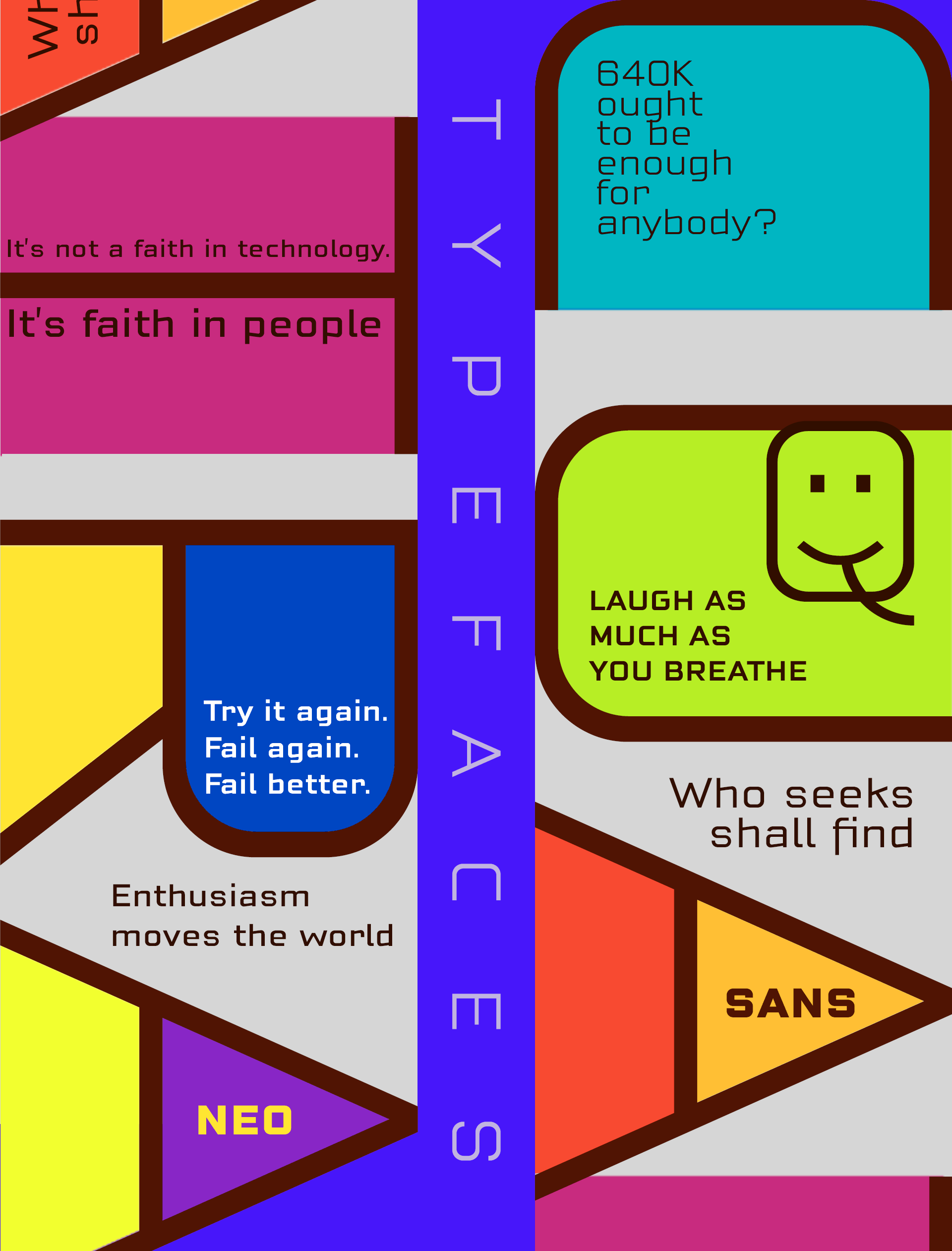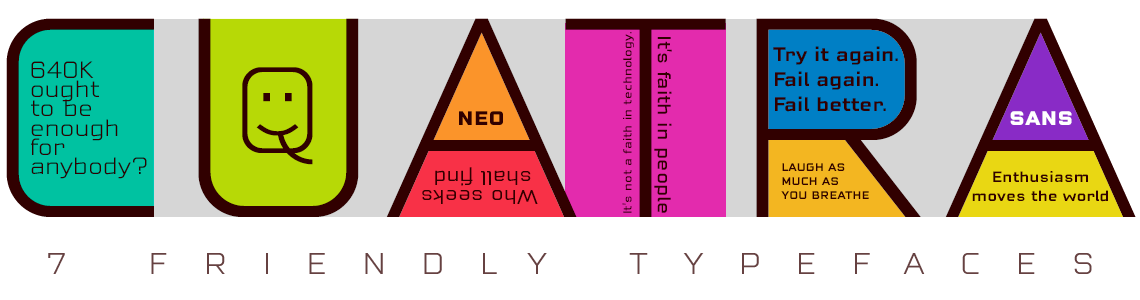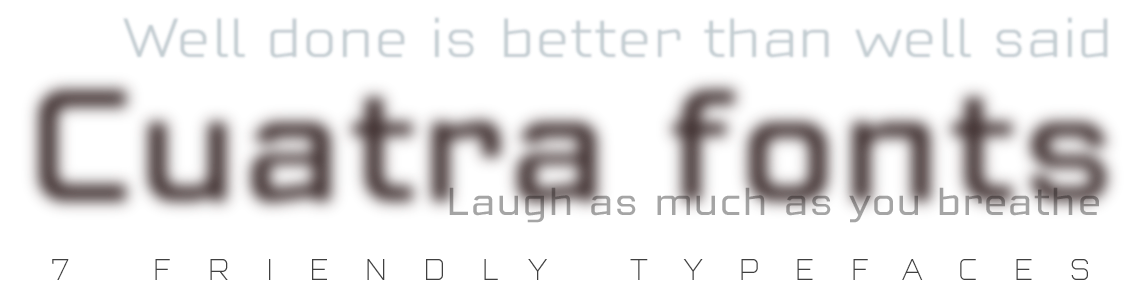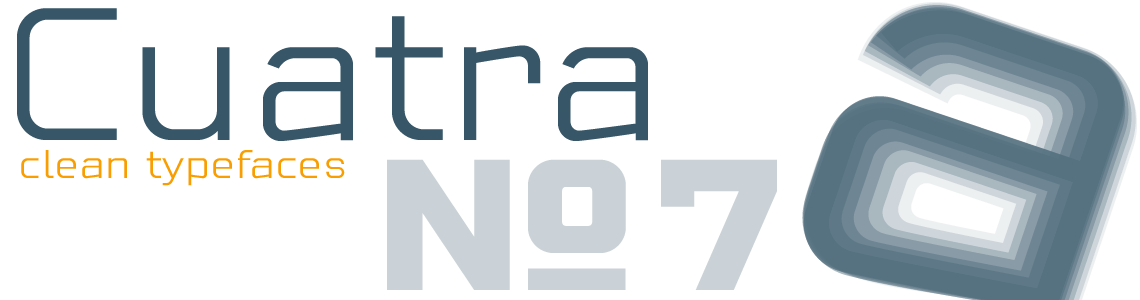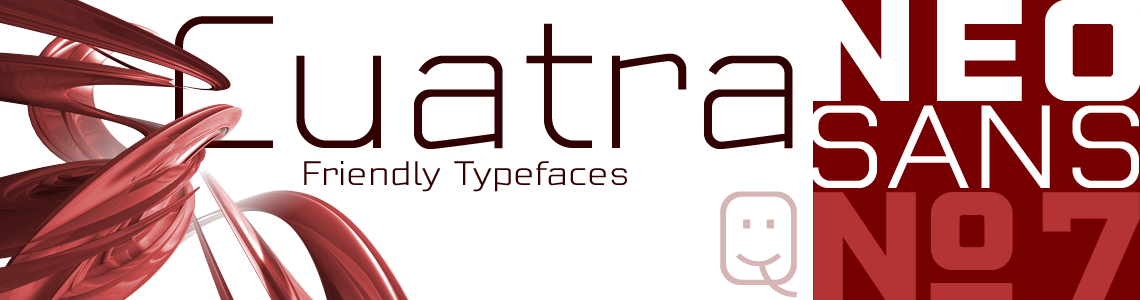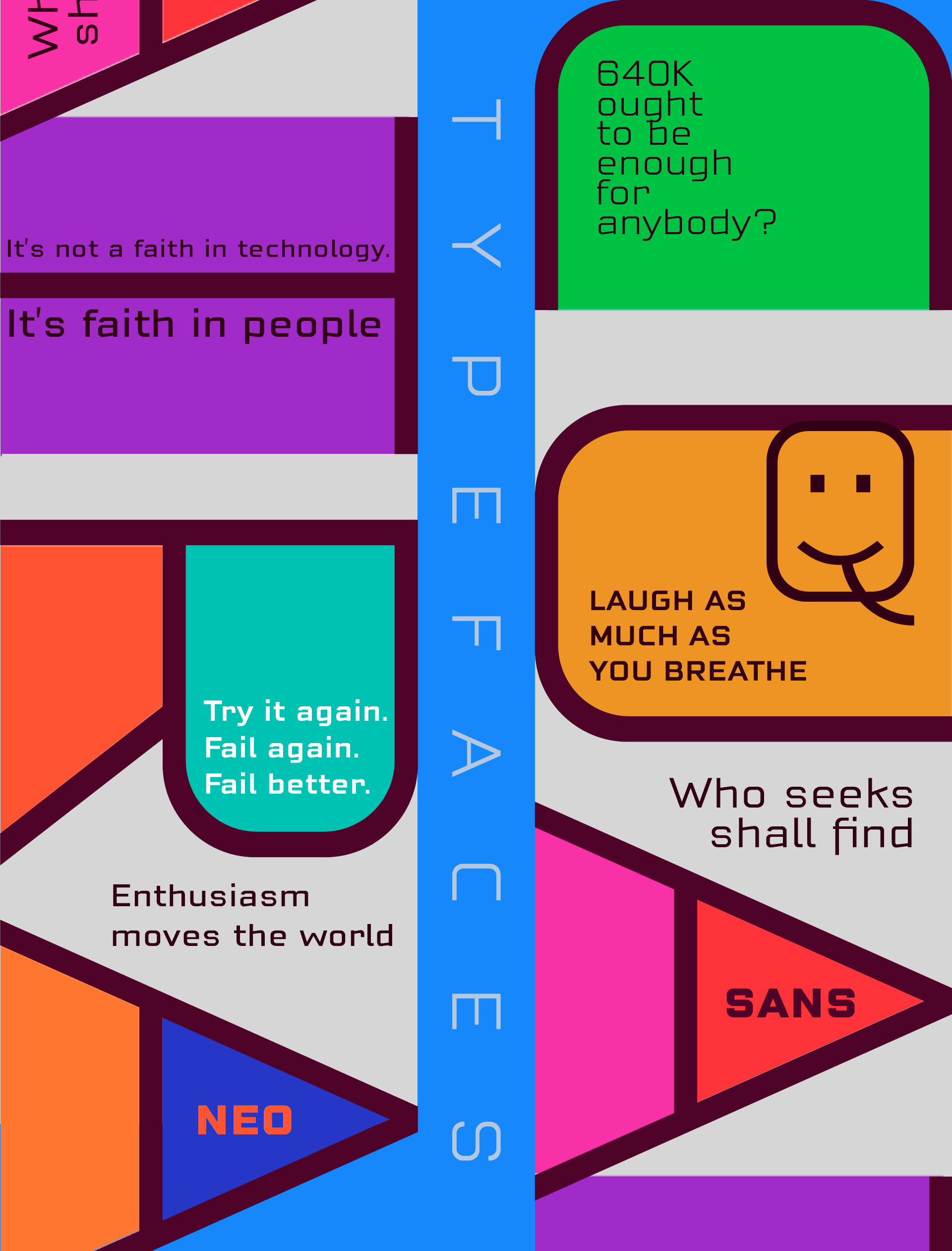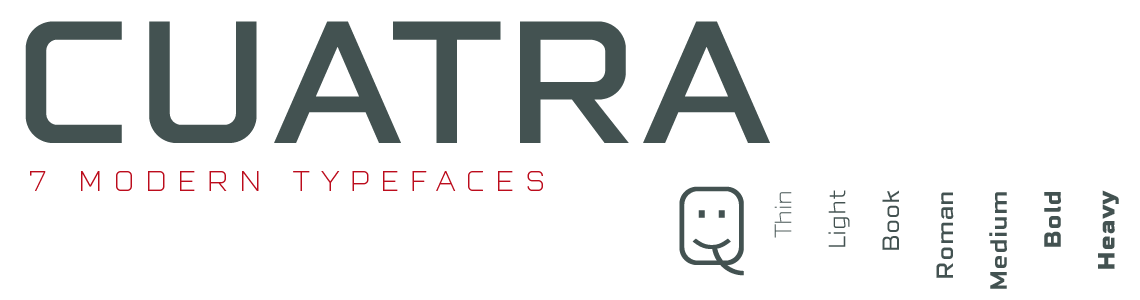
Tecno Sans Fonts
Estilo: Sans Serif, Geométrica, Corporativa, Cuadrada
Proporción: Thin, Light, Book, Roman, Medium, Bold & Heavy
Glyphs: 509
Año de publicación: 2018.
Funciones OpenType: Additional languages, All Alternates, Alternate Annotation Forms, Capital Spacing, Denominators, Discretionary Ligatures, Extended Fractions, Historical Forms, Historical Ligatures, Inferiors, Kerning, Localized Forms, Numerators, Oldstyle Figures, Ordinals, Scientific Inferiors, Slashed Zero, Standard Ligatures, Subscript, Superior letters, Superiors, Superscript.
Latin Extended-A & Open Type Features
Incluyen el símbolo del Bitcoin: b# (b # )
Las fuentes Cuatra Tecno disponen en su versión comercial de un juego de 509 glifos (Latin Extended-A), con soporte para cualquier idioma europeo o centro europeo. Cuatra Sans también incluye funciones OpenType (Compatibles con InDesign, QuarkXpress, Photoshop e Illustrator.